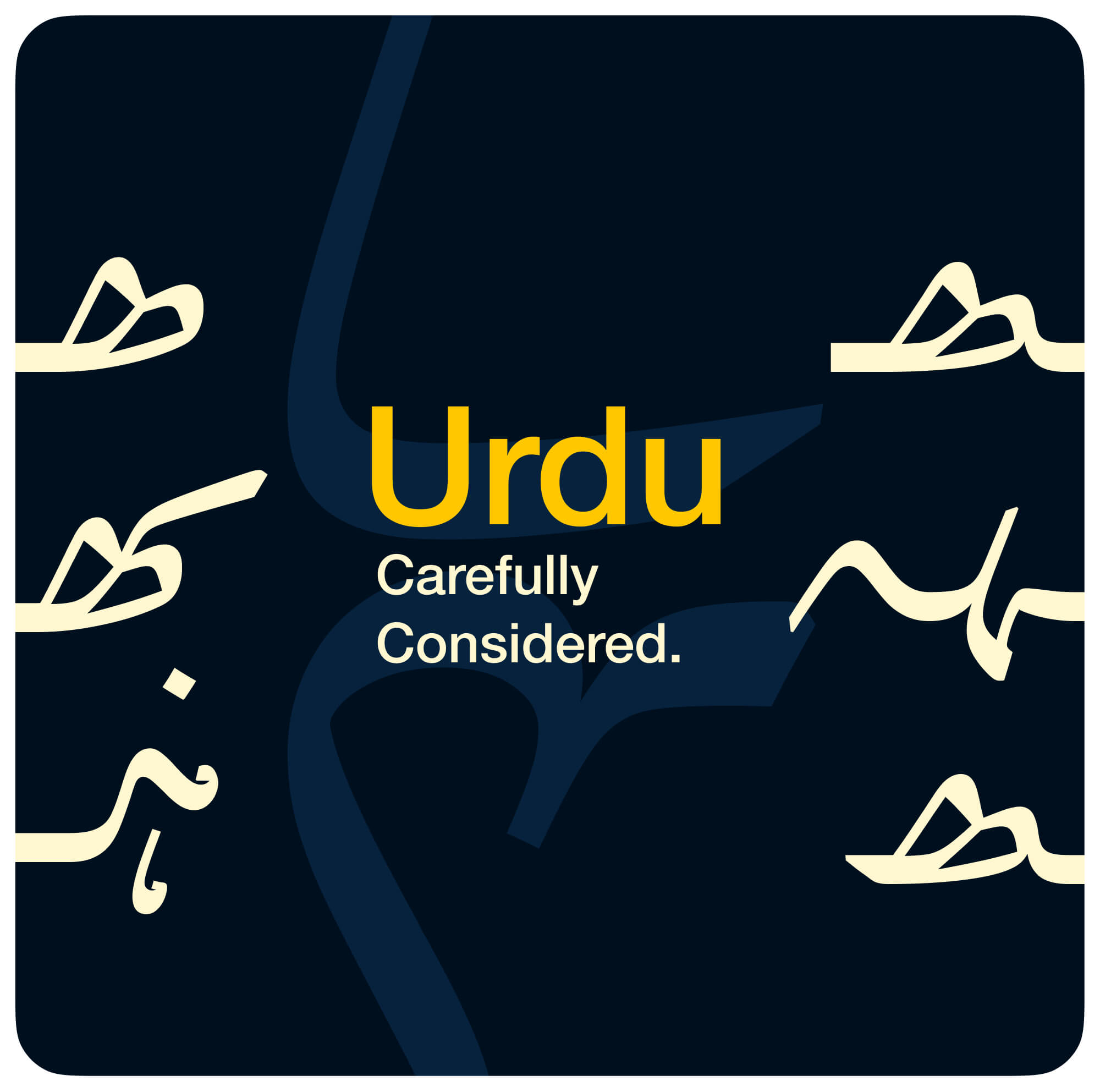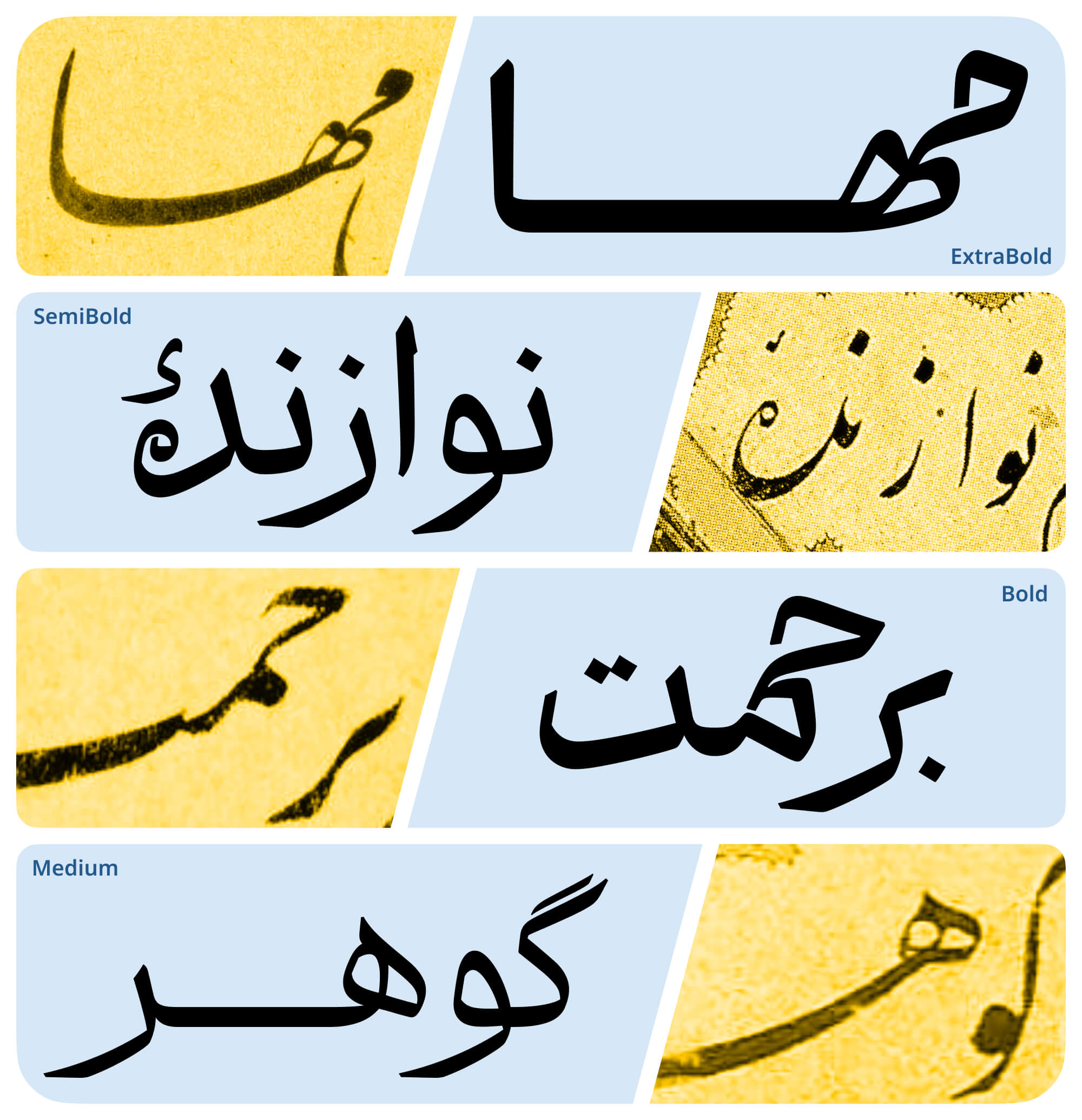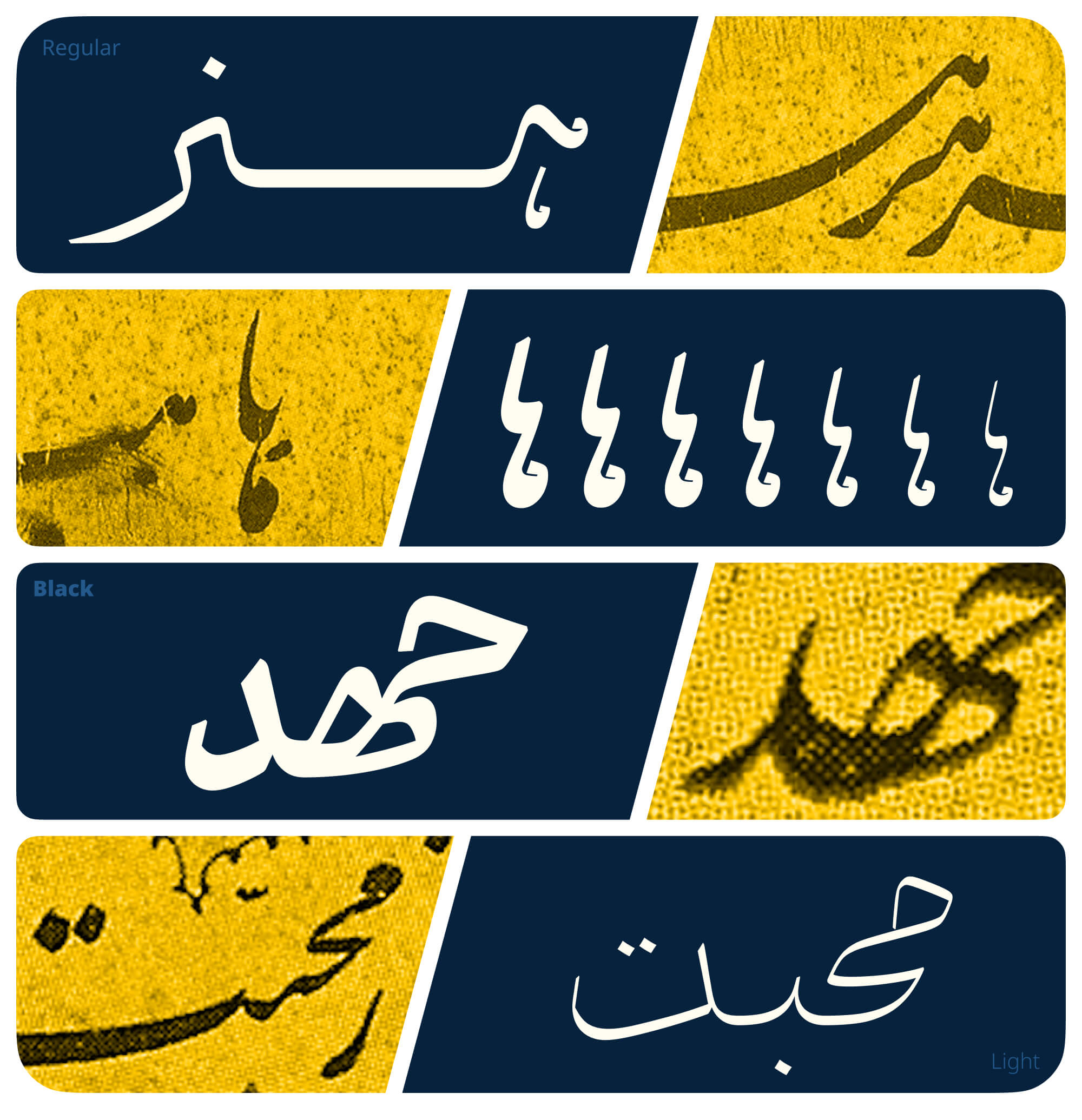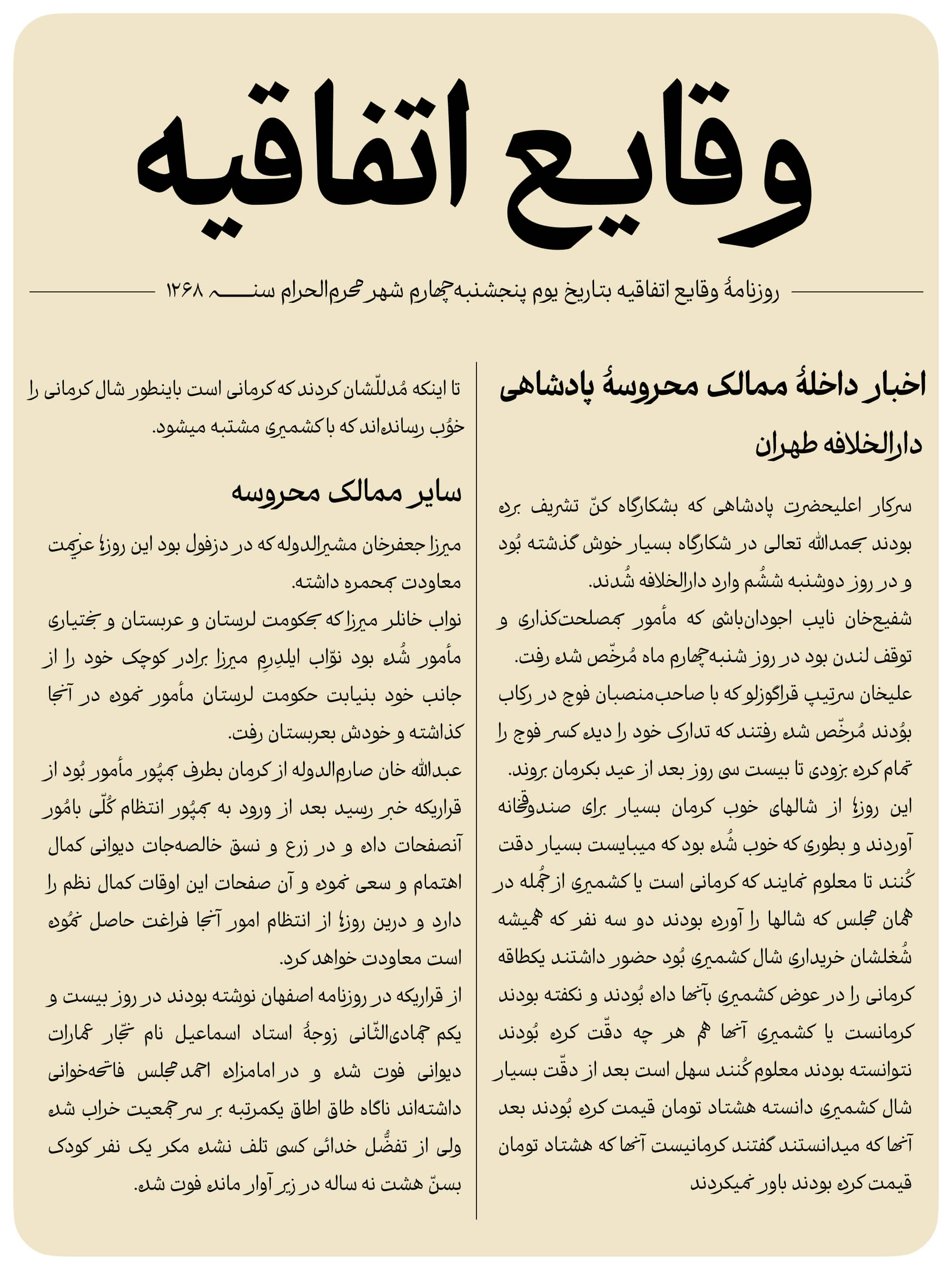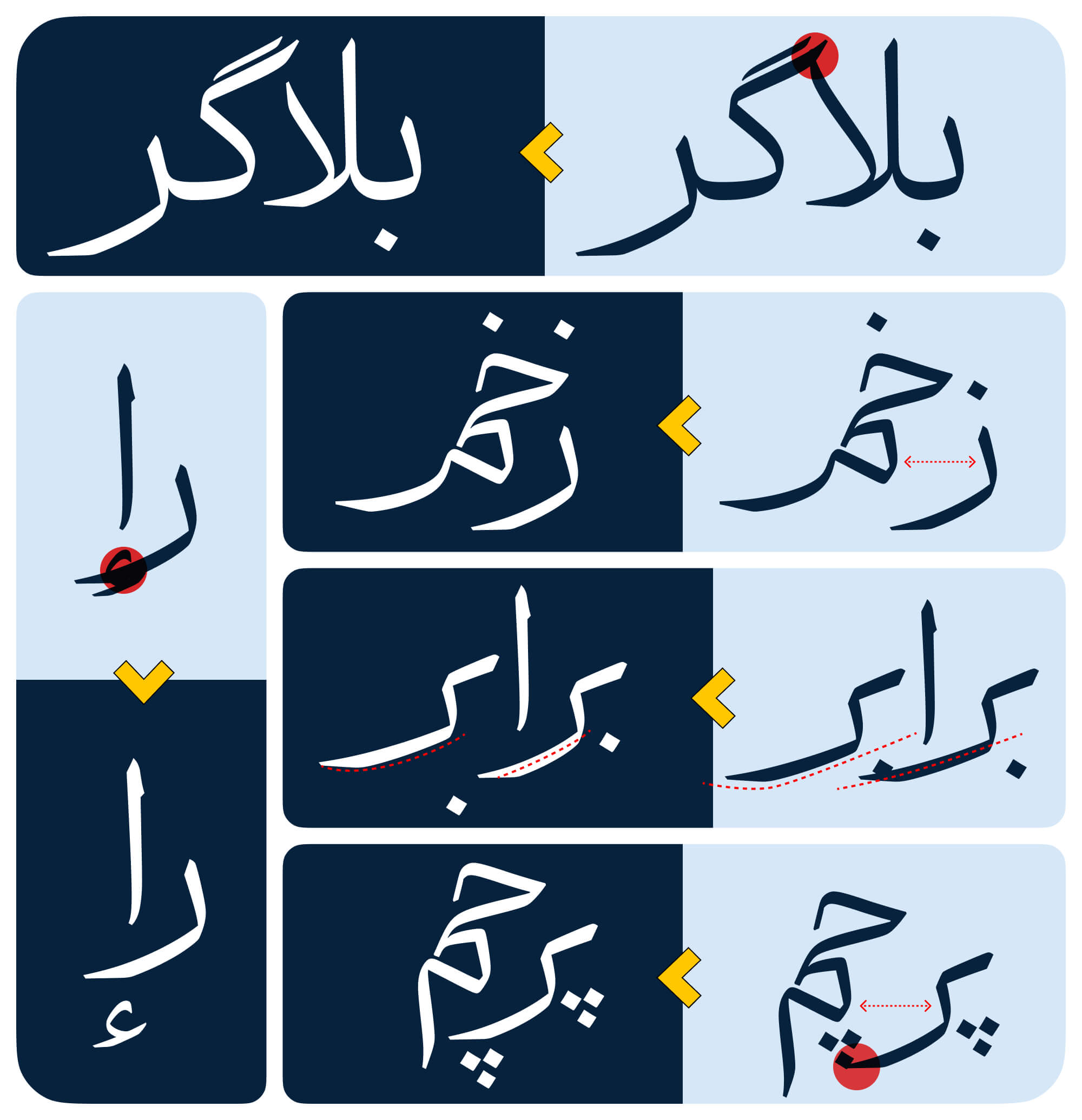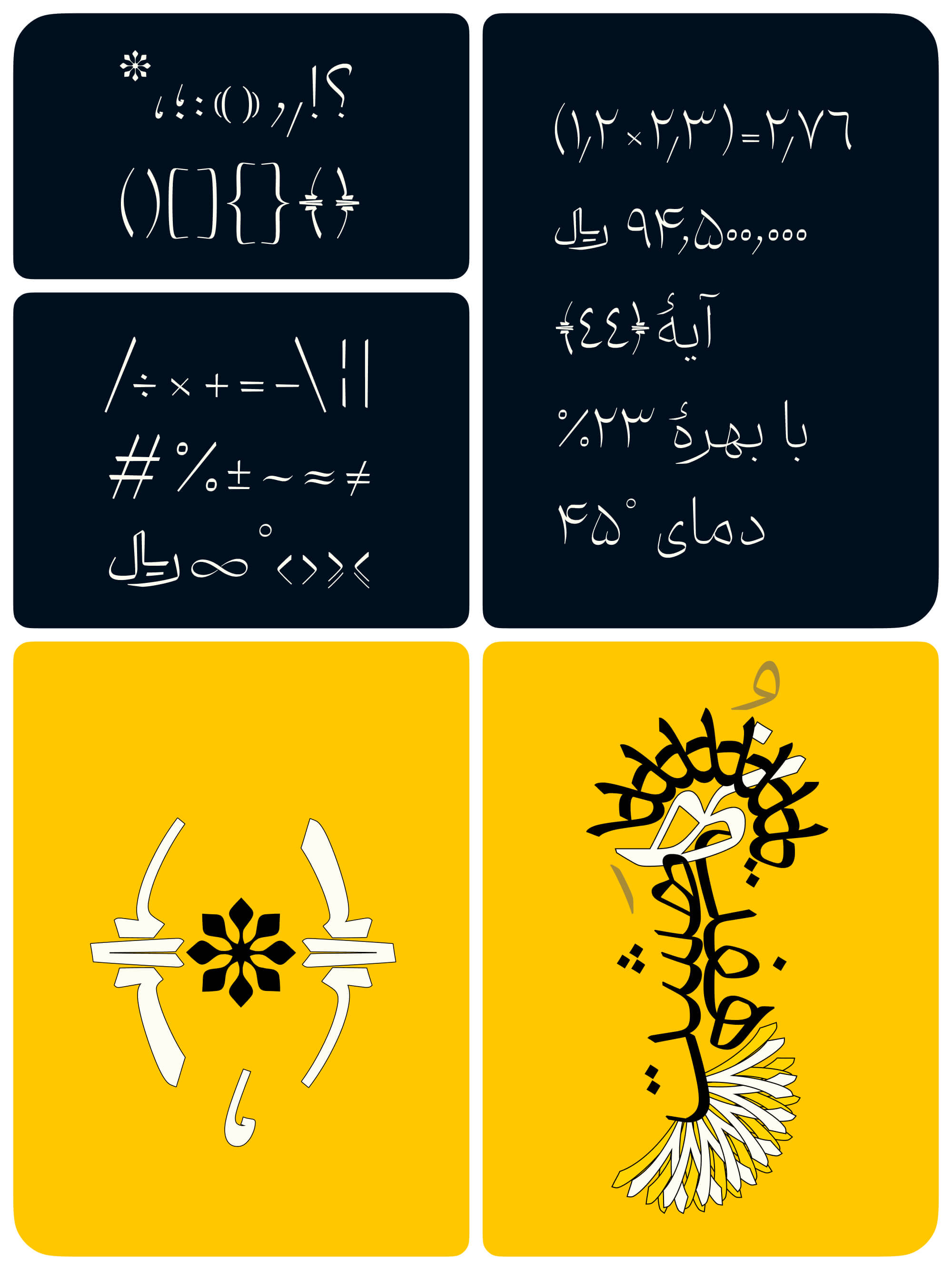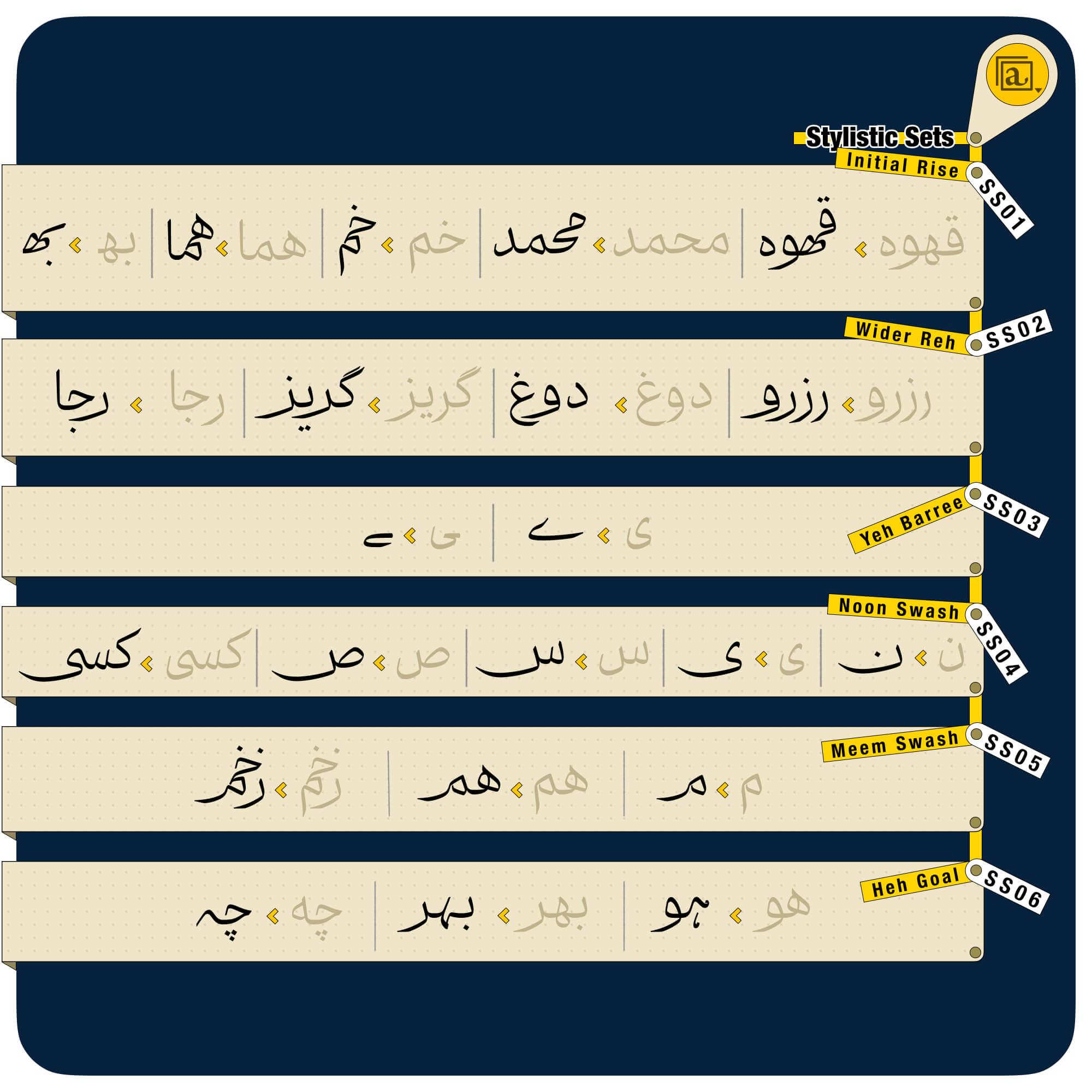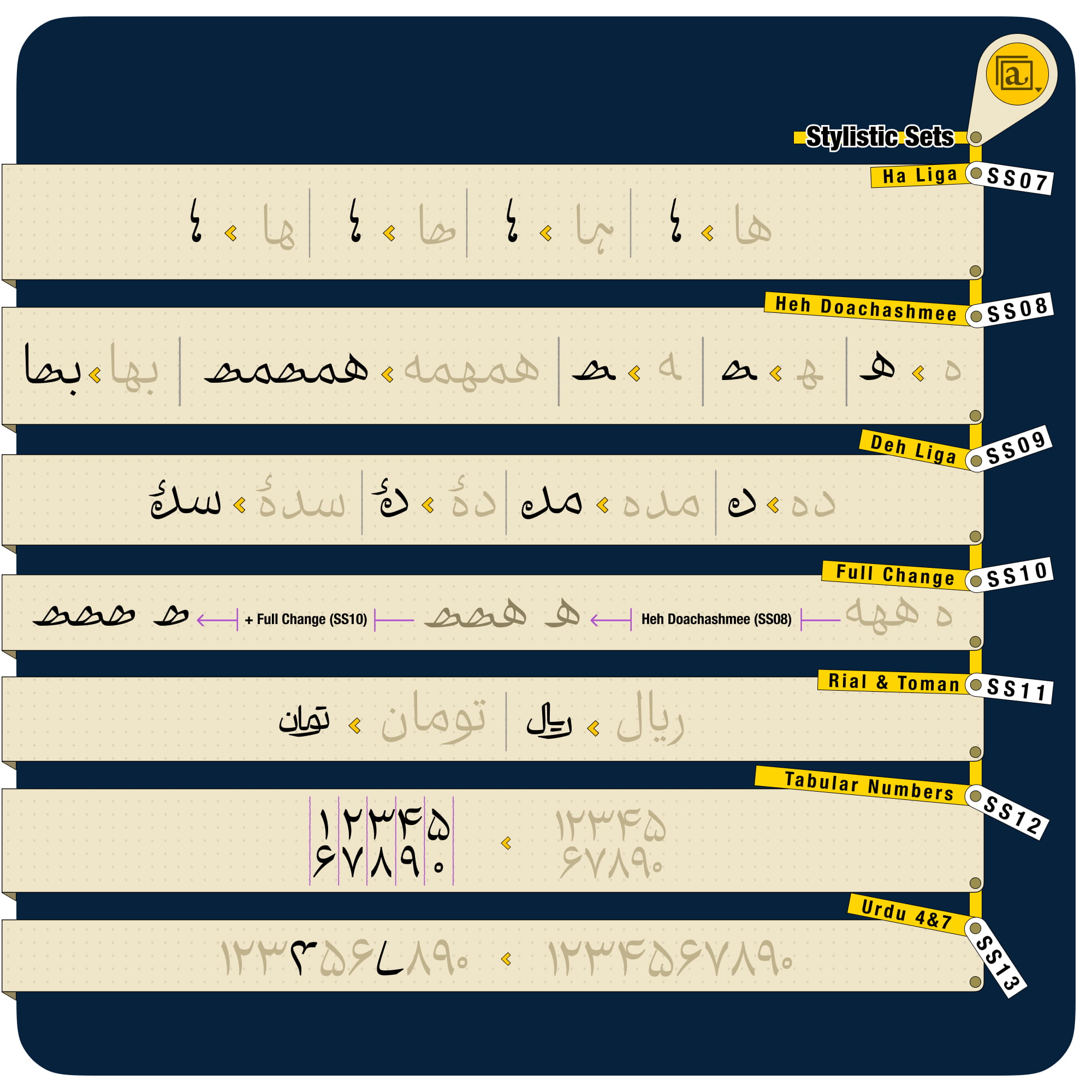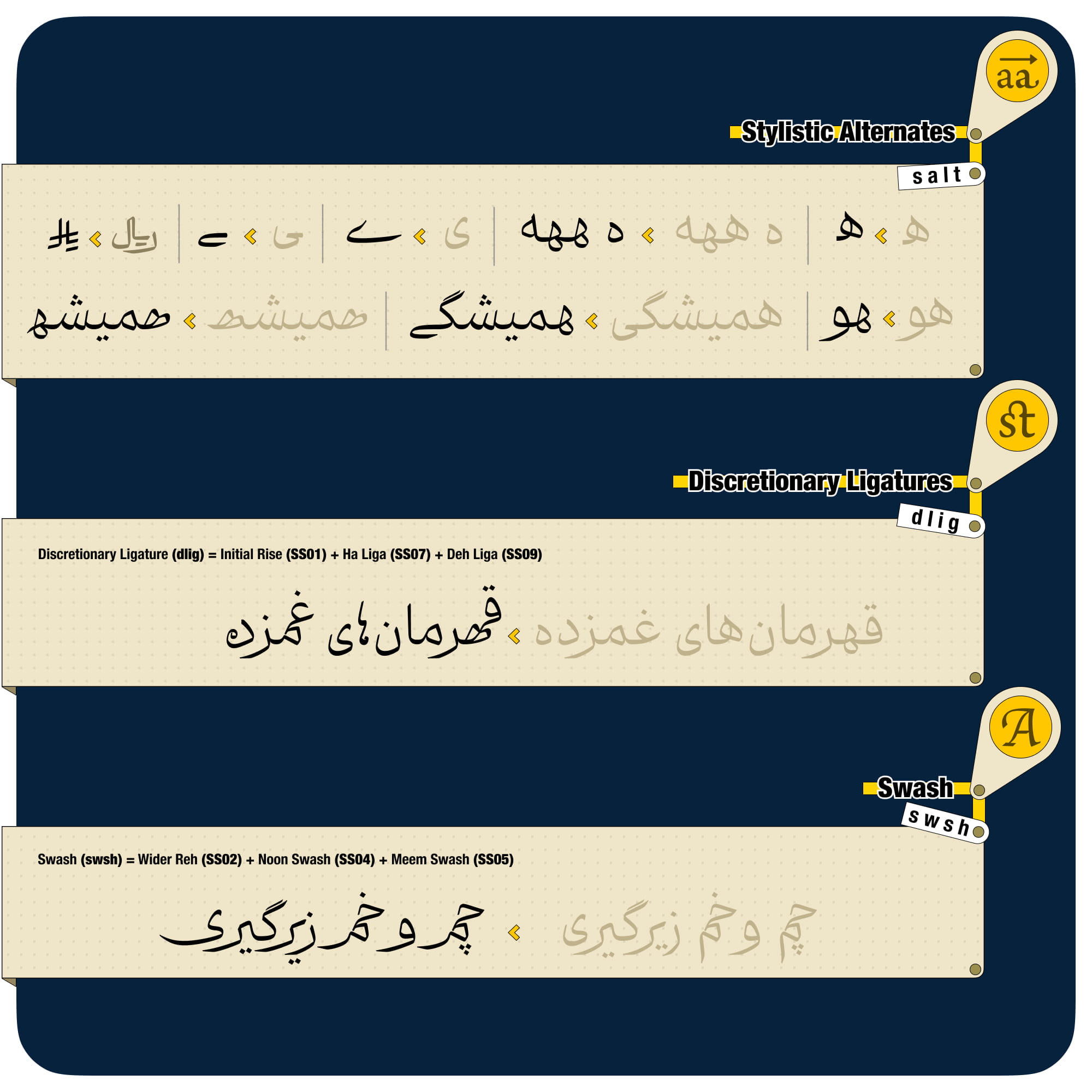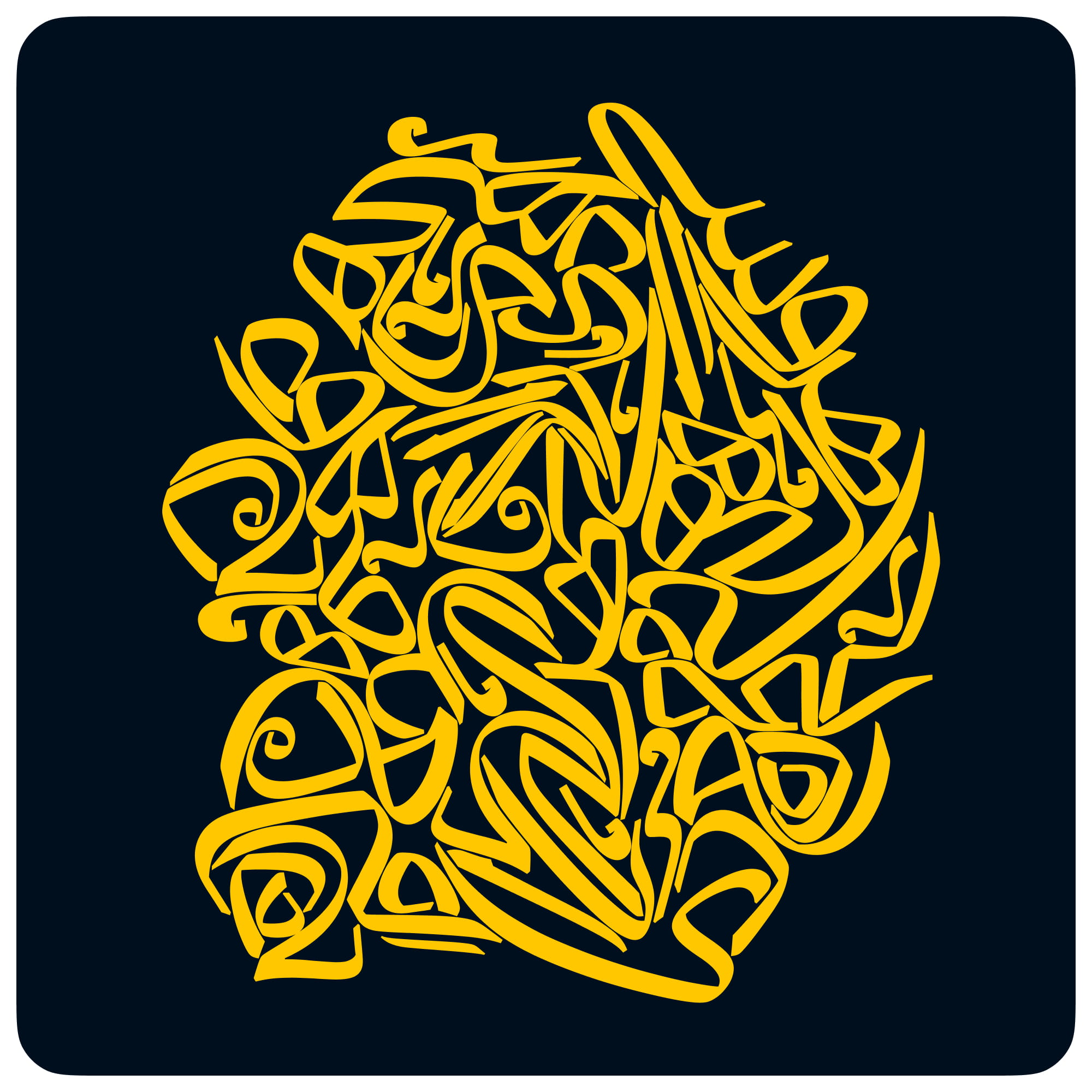
فونت نوزده
ایدهٔ شکل‌گیری فونت نوزده در ابتدا با هدف طراحی یک فونت متنی با برداشتی آزاد از خط محقق شکل گرفت؛ برداشتی که در عین وفاداری به روح این خط، تنها به بخشی از ظرایف و ویژگی‌های آن نظر داشت. نخستین اتودهای نوزده در سال ۱۳۹۸ شکل گرفت. پروژه پس از وقفه‌ای کوتاه، در سال ۱۴۰۱ از سر گرفته شد و طراحی حروف آن این‌بار با عبور از فیلتر نستعلیق ادامه یافت؛ مسیری که به تدریج شخصیت بصری فونت را شکل داد و به تکمیل نخستین وزن آن انجامید. پس از آن، طراحی وزن‌های دیگر به‌صورت پراکنده دنبال شد و در طی این مسیر، فرم بسیاری از حروف دستخوش تغییر، بازنگری و تکامل شد.
در سال ۱۴۰۴، فونت نوزده با افزودن مجموعه‌ای گسترده از ترکیبات جایگزین و سرهم‌نویسی‌هایی با حال‌وهوای نستعلیق، به شخصیت پخته‌تری رسید و از ایدهٔ اولیهٔ خود فاصله گرفت تا به تایپ‌فیسی مستقل و متمایز بدل شود.
زمان بسیاری صرف طراحی، بازطراحی و پرداخت جزئیات فونت نوزده شده است. بارها در ظرایف حروف و ترکیبات آن مکث کردم، از نزدیک به جزئیات نگاه کردم و سپس با فاصله‌ای بیشتر به کلیت آن بازگشتم؛ تا میان جزئیات و تصویر کلی، میان ظرافت و کارکرد، تعادلی دقیق برقرار شود. حاصل این فرایند، فونتی است که تلاش شده هم از منظر طراحی و هم از نظر توسعهٔ فنی، تا حد امکان سنجیده و کم‌خطا باشد. برای پوشش طیف گسترده‌ای از موقعیت‌های زبانی و ترکیب‌های ممکن، بیش از ۱۲۰۰ گلیف در هر وزن جای گرفته است.
در تمام مراحل طراحی و توسعه‌ی فونت نوزده، خوانایی در متون طولانی و اندازه‌های کوچک یکی از ملاحظات اصلی بوده است. جزئیات، هرچند بخش مهمی از شخصیت نوزده را می‌سازند، نباید بر رسالت اصلی یک فونت متنی غلبه کنند. ترکیبات متنوع و امکانات گستردهٔ آن نیز با همین نگاه طراحی شده‌اند؛ به‌گونه‌ای که افزوده‌های بصری، همواره در خدمت متن باقی بمانند.
نوزده تایپ‌فیسی چندوجهی است؛ می‌تواند در تیترها و متون کوتاه حضوری چشمگیر داشته باشد، در عین حال از عهدهٔ متون طولانی نشریات و کتاب‌های چاپی برآید. در فضای دیجیتال نیز می‌تواند انتخابی کلاسیک و در عین حال جسورانه برای وب‌سایت‌ها و اپلیکیشن‌ها باشد.
مجموعهٔ متنوع ترکیبات و فرم‌های جایگزین نوزده، امکان دیگری نیز پیش روی طراح می‌گذارد؛ استفاده از آن‌ها برای خلق لوگوتایپ‌هایی با شخصیت و بیان بصری منحصربه‌فرد
توازی پاشنه‌‌ی «ر» و «و»
در خطوطی چون محقق، پاشنه‌های بلندِ «ر» و «و» از ویژگی‌های شاخص ساختاری‌اند و توازی آن‌ها نقش مهمی در حفظ ریتم و جریان نوشتار دارد.
در فونت نوزده، این ویژگی با پنج فرم و اندازهٔ متنوع برای پاشنهٔ «ر» و «و» بازآفرینی شده است؛ به‌گونه‌ای که ضمن حفظ این توازی، طول عمودی حروف کنترل شود و تعادل بصری، ریتم و خوانایی متن آسیب نبیند.
یکی از فرم‌های شاخص «ه» در نستعلیق، هٔ ذوصادین است؛ فرمی خاص و زیبا که در فونت‌های مدرنِ غیرنستعلیق کمتر بازآفرینی شده است. تا آنجا که در نمونه‌های شناخته‌شده دیده‌ایم، نوزده از نخستین فونت‌هایی است که این فرم را در ساختاری غیرنستعلیقی بازآفرینی و با زبان بصری خود متناسب کرده است؛ رویکردی که دربارهٔ هٔ ویرگولی نیز به کار گرفته شده است.
ایجاد این تناسب فرمی، یکی از چالش‌های مسیر طراحی فونت نوزده بود.
فونت نوزده
اهمیت این دو فرم ه در نوشتار اردو بیشتر آشکار می‌شود؛ جایی که تمایز میان «ه» و «ھ» در نظام نوشتاری نقش مشخصی دارد.
فونت نوزده مجموعه‌ای گسترده از ترکیبات جایگزین را در اختیار می‌گذارد. این ترکیبات به‌صورت مستقل در Stylistic Sets ارائه شده‌اند و برخی از گزینه‌های کاربردی‌تر نیز برای دسترسی آسان‌تر در dlig و swash قرار گرفته‌اند.
فونت نوزده در دو نسخهٔ Base و AOL (Always-On Ligatures) ارائه می‌شود. هر دو نسخه از نظر امکانات و ترکیبات جایگزین یکسان‌اند؛ تفاوت در این است که در نسخهٔ AOL، برخی لیگچرهای رایج و ترکیبات ویژهٔ نوزده به‌صورت پیش‌فرض و اجباری فعال هستند. این ویژگی باعث می‌شود ترکیبات موردنظر حتی در محیط‌هایی که از قابلیت‌های OpenType به‌طور کامل پشتیبانی نمی‌کنند هم به‌صورت خودکار اعمال شوند.